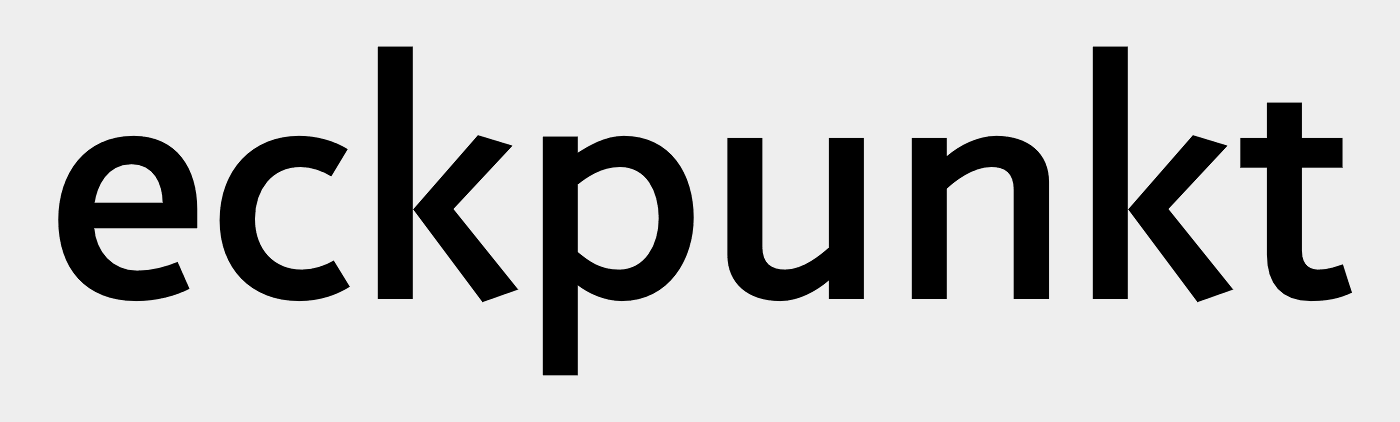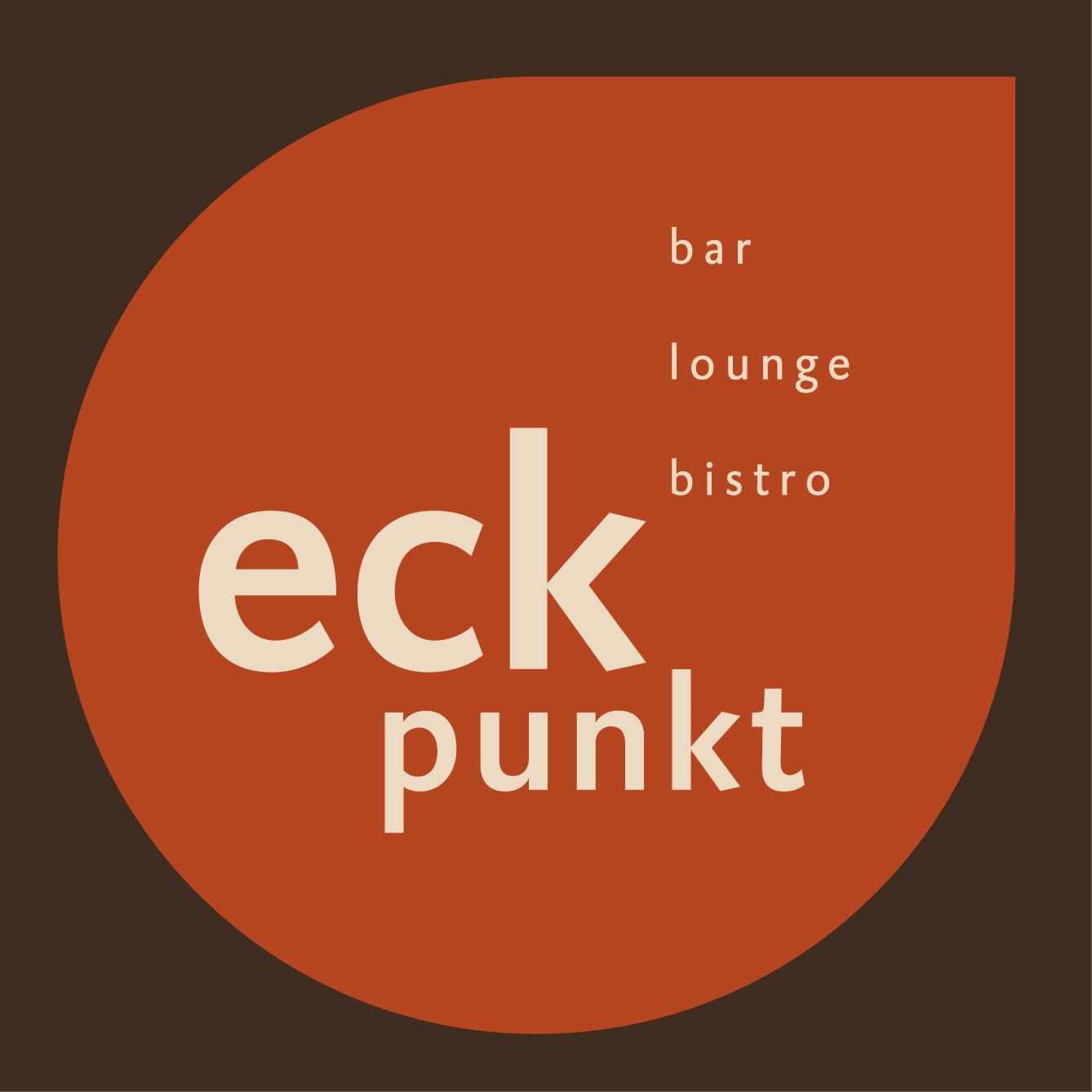
Wer kennt diese Schrift? (eckpunkt)
die Schrift sieht auf ersten Blick aus wie eine Syntax, aber sie ist es leider nicht. Ich bin auf  http://www.identifont.com/ die ähnlichen Schriften durchgegangen http://www.identifont.com/find?similar=Syntax&q=Go  hatte aber leider keinen Erfolg. Als Ersatz wäre ggf. die breit und preiswert Verfügbare Syntax möglich, wenn sonst alle Stricke reißen.
Die Syntax hatte ich auch schon gefunden. Die Jigsaw ist schon sehr ähnlich, aber leider ist sie es auch nicht. Ich werde wohl selber Hand anlegen müssen, aber viele Dank :-*
Vielleicht wurde das auch aus mehreren Schriften zusammen gestückelt? Ich bin mir nicht sicher, ob das t oben so gut zum punk passt. :-?
Über das t bin ich auch gestolpert, das sieht wahrlich wie aus einer anderen Schriftart aus.